DynaFont × Christmas 2017 クリスマスプレゼントキャンペーン
ダイナコムウェアは本日12月1日から「DynaFont × Christmas 2017 クリスマスプレゼントキャンペーン」を開催している。
書体と文字に関するアンケートに答えると抽選で30名にダイナコムウェア2018年オリジナル卓上カレンダー「DynaFont × 枕草子」を含むDynaFontステーショナリーセットがプレゼントされる。
応募方法は専用のキャンペーン応募アンケートサイトにて行われる。応募期間は2017年12月1日(金)から12月15日(金)までとなっている。
ダイナコムウェア2018年オリジナル卓上カレンダー「DynaFont × 枕草子」
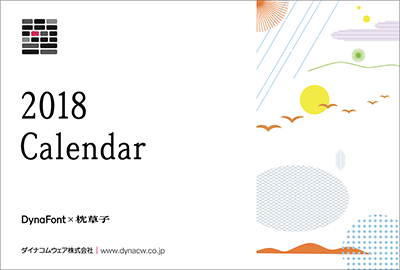
古典文学の傑作である「枕草子」を月別にそれぞれ12種類のダイナフォントを使用して文字組みしたカレンダー。1年を通してダイナフォントの魅力を感じられるカレンダーとのこと。その他に鉛筆、マスキングテープ、付箋などをセットにしてプレゼントされるようだ。
カレンダーに使用された書体は麗雅宋、古籍糸柳、古籍木蘭、角POP、娥眉明朝体、古籍黒檀、古籍銀杏、唐風隷書体、古籍真竹、ロマン雪、クラフト墨、金文体の12書体。
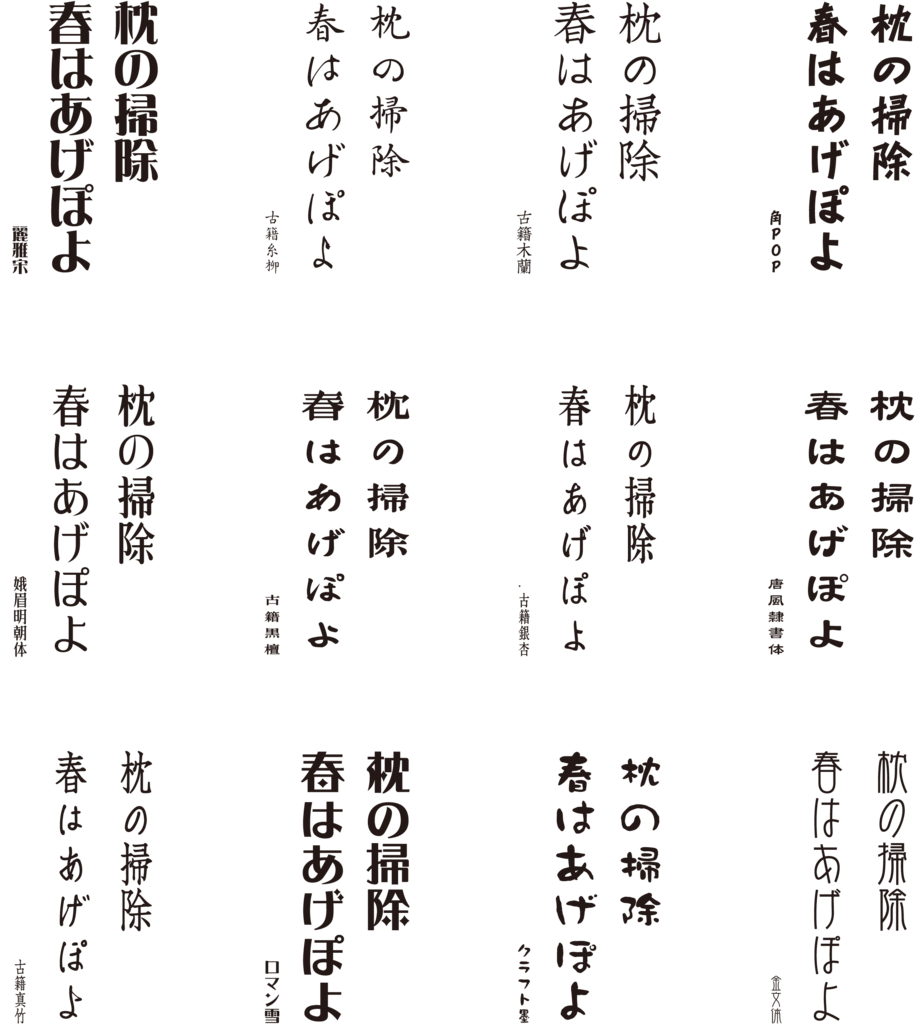
「DynaFont × 枕草子」の文字組み採用された12書体について
麗雅宋
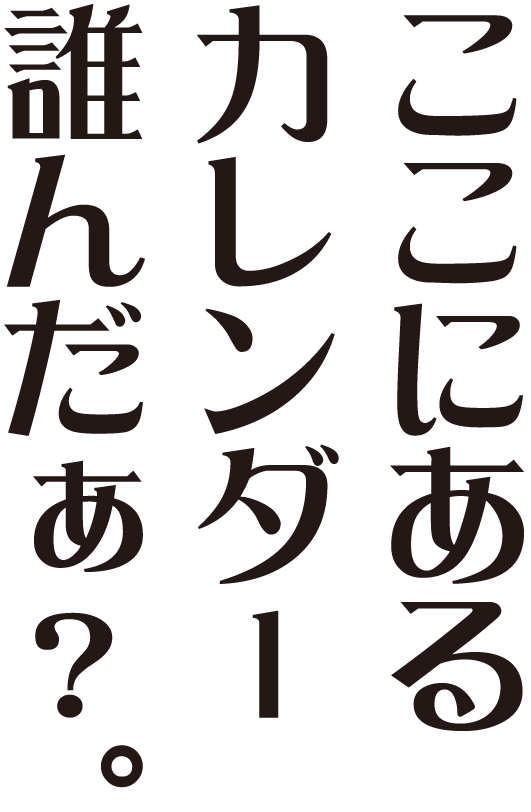
看板やテレビのテロップなど色々な場面で見かける書体。明朝体をベースに真四角なイメージをもたせている。
古籍糸柳
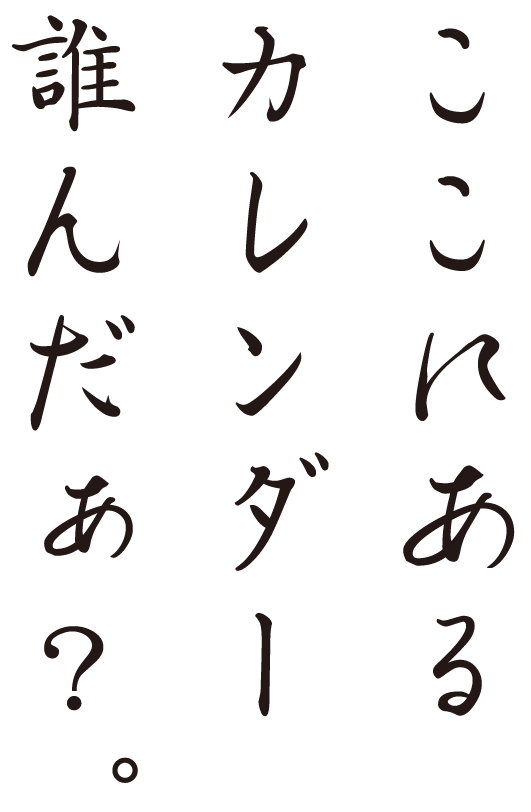
中国の古籍「四庫全書」をもとに開発された書体。「四庫全書」の文字は、楷書の字形が細い柳のように生い茂り、豊かな活力を表現している。特に左はらい、右はらいのストロークが柳の葉っぱのように柔らかく、風に揺られているような印象を与える。
古籍木蘭
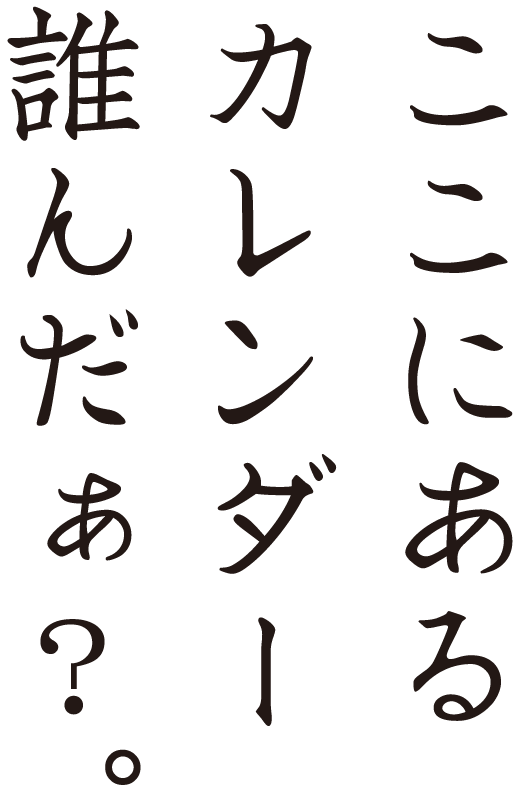
「元豊類稿」の「聚珍倣宋」版の活字を印刷した復刻版の古籍をデジタル化した書体。広々とした木蘭の木のような幅を持ち、楷書の筆形が花びらのように伸びている。
角POP
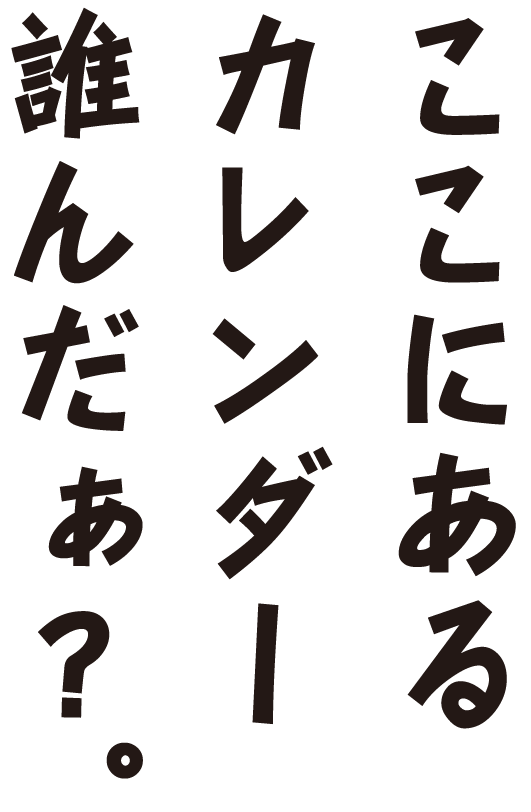
伝統楷書をベースにして、角張った字形を採用した書体。どことなくモダンな風格を備えており、タイトルやロゴといった部分での使用に適している。
娥眉明朝体
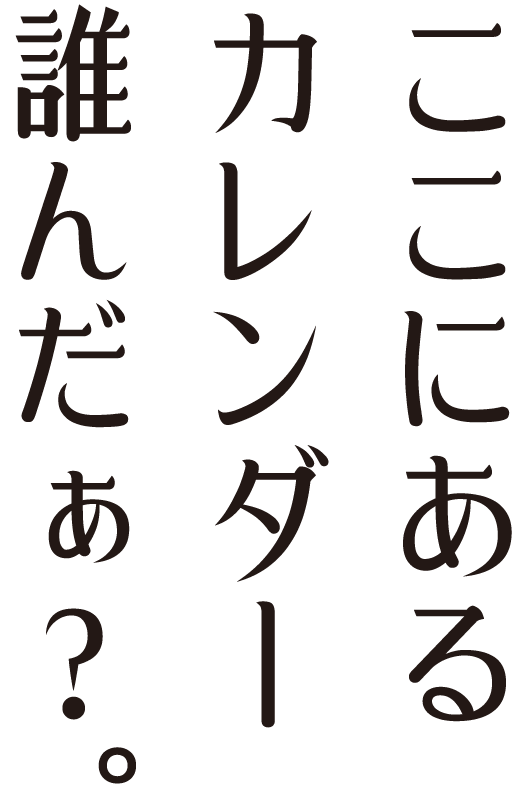
細長く弧を描いた眉の形をイメージしたストロークから洗練された女性の柔らかさや優しさを表現した明朝体。
古籍黒檀
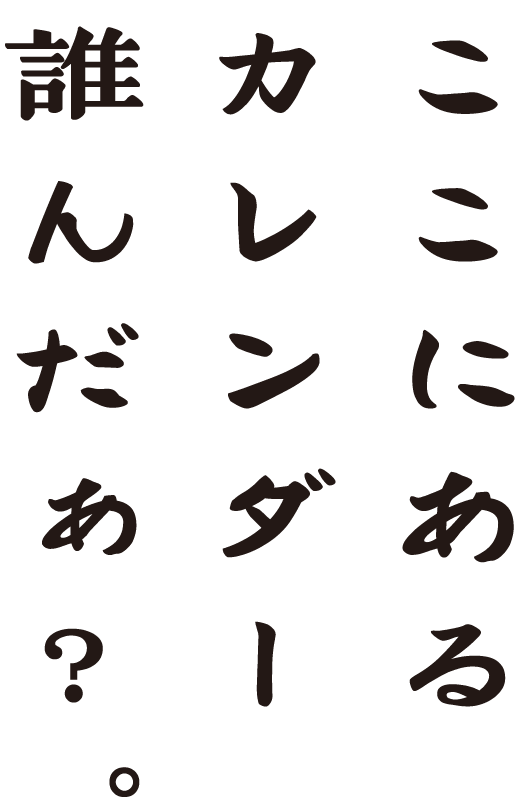
中国の古籍「范伯子集」の書帖をもとに開発された書体。「范伯子集」の文字は、扁平な字形と重厚なストロークが特徴で転折が力強く彫刻の質感のような雰囲気が溢れている。
古籍銀杏
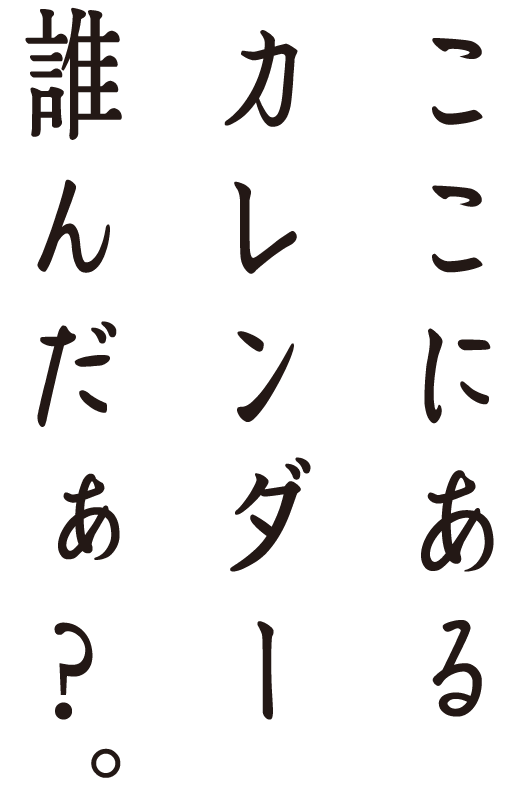
中国の古籍「天工開物」をモチーフとして開発された書体。「天工開物」の文字は、半円形となったストロークが繊細で、銀杏の葉っぱのような優雅さがある。
唐風隷書体
横長で太く扁平な字形がどっしりと落ち着きを感じさせる隷書体。
古籍真竹
文字の重心が低く、ストロークの転折が竹の節のようで、力強さとしなやかさが同居し、悠然とした表情が窺えるストローク先端が細い真竹のように見える書体。
ロマン雪
1925年の藤原太一著書による『図案化せる実用文字』から着想を得て、図中の婦人の華麗な装いや愛らしいスタイルをヒントにして、大正末期から昭和初期にかけての古典ロマンの雰囲気を再現した書体。
クラフト墨
書道元来の構成や書き方に変化を加え、文字の面白さや破調を表現した書体。線の長さや「へん」「つくり」などの部首に字形を崩す程の変化を加え、空間の取り方も独特であり、丸く豊かな運びによって可愛く、リラックスした雰囲気を引き出されている。
金文体
中国戦国時代の“中山王方壺”に鋳込み刻まれた金文を元にした縦長のオリエンタルなフォルムが特長の書体。
2014年度グッドデザイン賞を受賞「古籍五書体」
DynaFont古籍書体シリーズとは、台湾の「故宮博物院」に収録された古籍と復刻版の古籍の出版品から「元豊類稿」「唐百家詩選」「天工開物」「四庫全書」「范伯子集」の五冊に書かれた文字をベースに開発されたデジタル書体である。歴史的価値が高く文化性に優れた古籍文字に、長期の開発期間を費やしデザイン性を追求しブラッシュアップさせた事により、文化性と芸術性の高さが融合された稀有な書体として完成に至った。
「古籍木蘭」、「古籍真竹」、「古籍銀杏」、「古籍糸柳」、「古籍黒檀」の古籍の冠が名づけられた五つの書体は、それぞれに異なる特徴を有しながらも、どこか古風な情緒が醸し出されており、古籍書体シリーズとしての一体感を感じさせる書体として大きく評価され、2014年度グッドデザイン賞を受賞した。